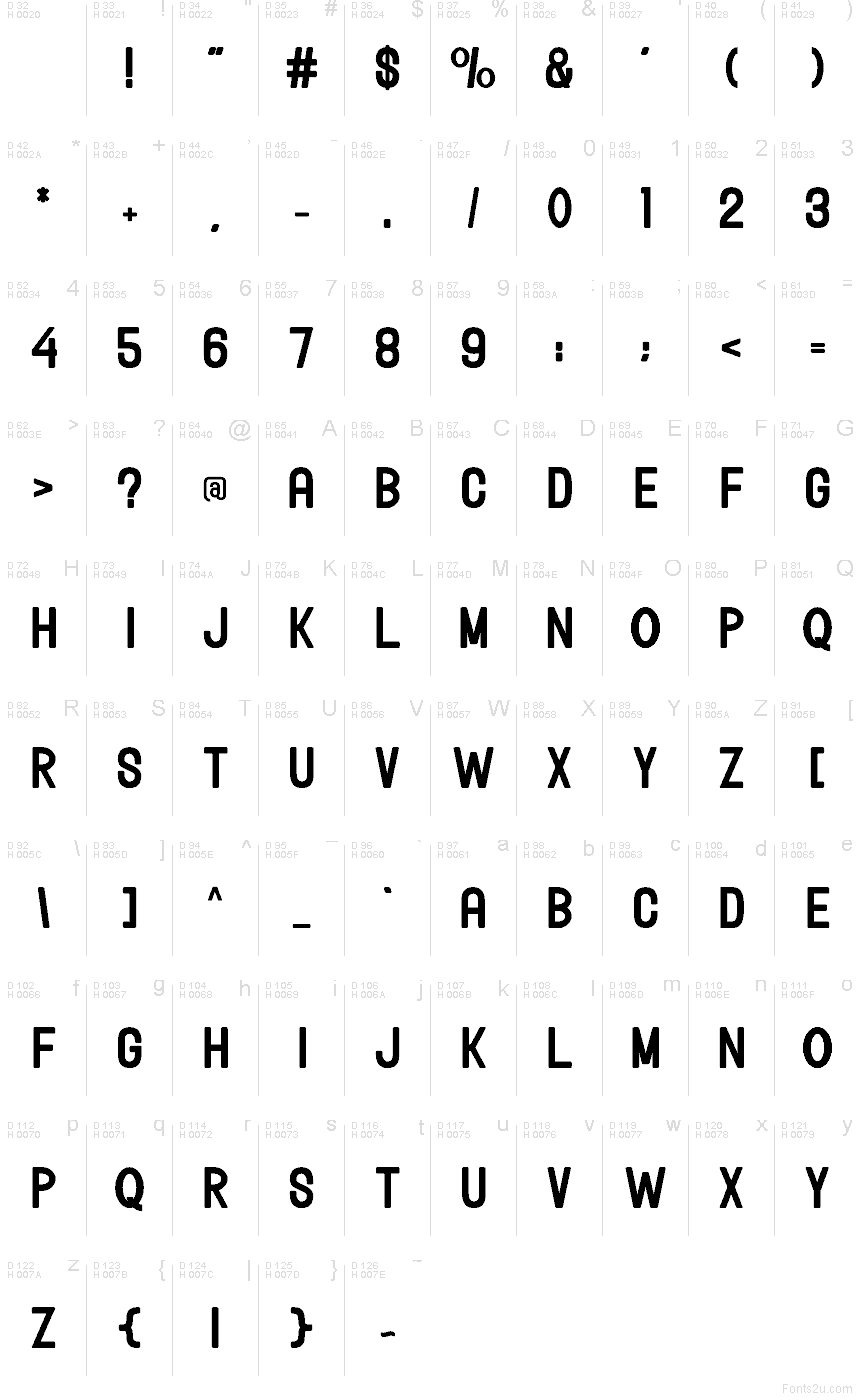
Coffe Break Regular
Coffe Break od Hyperactype Tim je bezpätkové písmo zdarma s výraznými, zaoblenými tvarmi, ktoré pôsobia, akoby boli opečiatkované na kelímku s kávou. Jeho vysoká hmotnosť, štíhle proporcie a mäkké rohy dodávajú každému slovu útulný a prívetivý vzhľad, zatiaľ čo pevný rytmus udržuje nadpisy kompaktné a čitateľné. Písmená pôsobia robustne a trochu hravo, podobne ako nápisy v malej miestnej kaviarni.
S Coffe Break získa váš branding a grafické návrhy okamžite odvážny a priateľský hlas, ktorý je jasne čitateľný aj z diaľky. Tento font zdarma skvele vynikne na obaloch kávy, logách kaviarní, jedálnych lístkoch, plagátoch, príspevkoch na sociálnych sieťach alebo reklamných predmetoch. Skombinujte ho s čistým, neutrálnym bezpätkovým písmom v menších textoch a nechajte rodinu Coffe Break, aby sa postarala o veľké titulky, ktoré okamžite upútajú pozornosť.